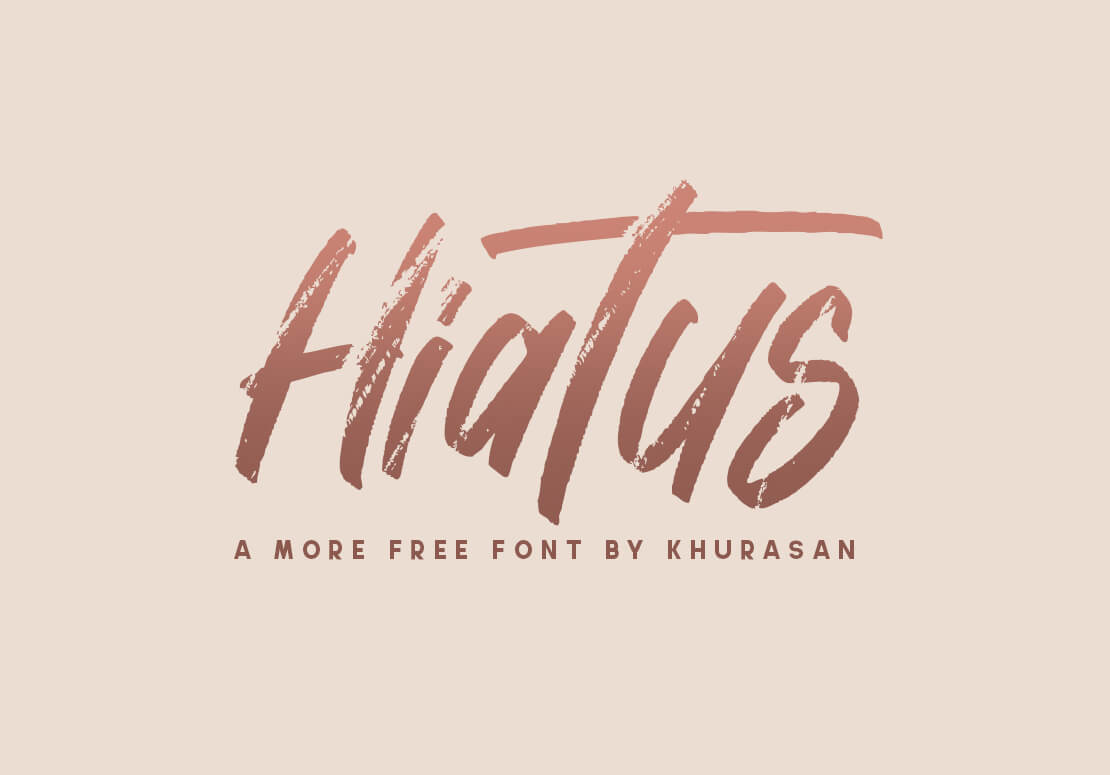
Hiatus
Von Khurasan Studio aus Indonesien kommt dieser expressive Free Font. Die Schriftart gibt es kostenlos im Opentype- und TrueType-Format zum Downloaden.